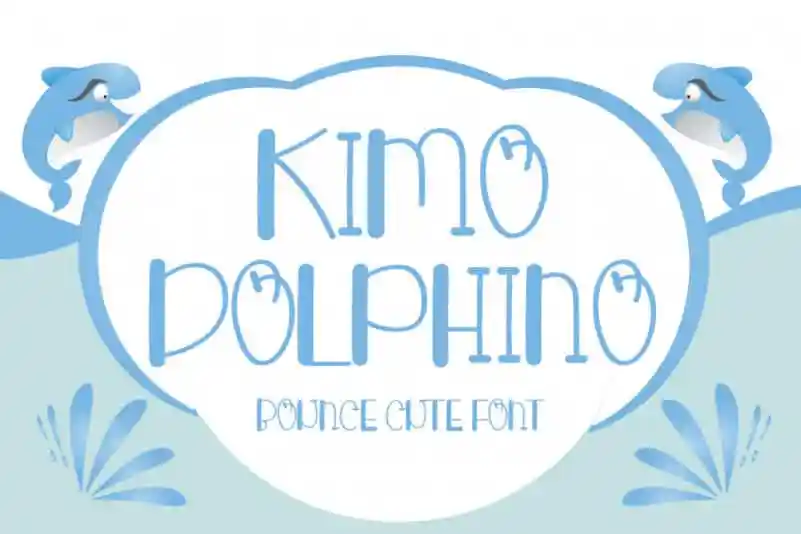
Kimo Dolphino Display Font – Download Grátis
A Kimo Dolphino Display Font é uma escolha ótima para quem busca um visual moderno e descontraído para seus projetos digitais. Ela mantém sua essência clássica, inspirada na calligrafia, enquanto se adapta bem ao que há de mais novo no design atual. Esta fonte tem uma grande versatilidade que vai agradar designers criativos de diversas áreas, desde os logotipos e cabeçalhos até as etiquetas e materiais para uso pessoal. Seu equilíbrio perfeito entre estilo clássico e modernidade fresca torna-a uma fonte ideal para aquela necessidade de um design único e inovador. A Kimo Dolphino Display Font é a escolha perfeita para aqueles que valorizam um resultado visual divertido e inconfundível.